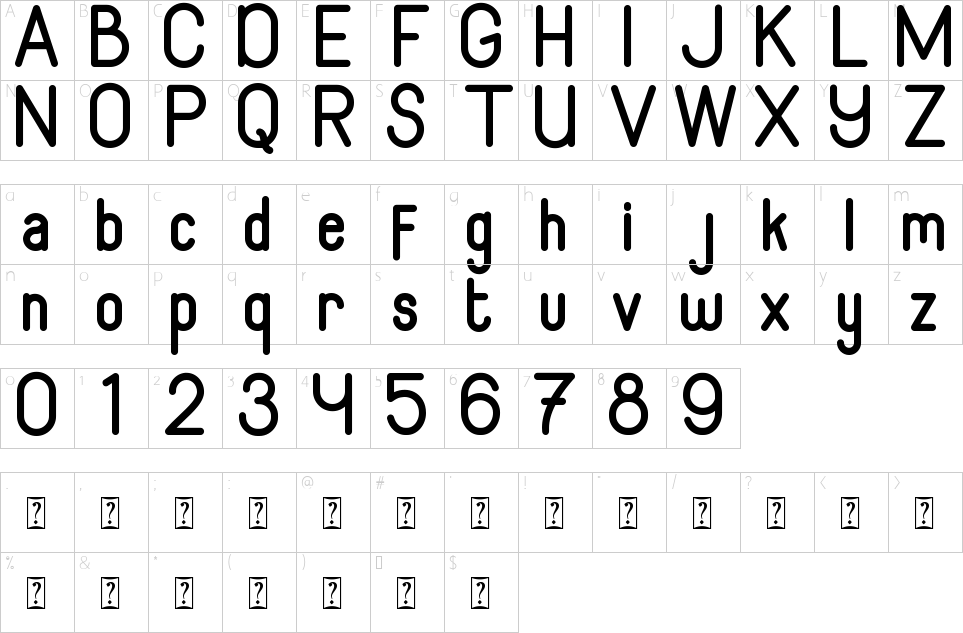
A fonte Algeko é uma escolha perfeita para designers e amantes da boa impressão. Desenhada pelo talentoso designer Alif Ryan Zulfikar, a Algeko traz uma combinação única de elegância e simplicidade. Esteve disponível gratuitamente para download, com mais de 2.529 pessoas optando por ela, o que indica a sua qualidade e versatilidade. A Algeko é uma fonte versátil, adequada para uso em diversos ambientes design, desde o layout de websites até editoriais de jornais. Com um design limpo e uma tipografia sofisticada, ela é uma ótima opção para qualquer projeto que busque um equilíbrio perfeito entre funcionalidade e beleza visual. A fonte Algeko não só oferece uma variedade de opções de estilo, como também mantém uma facilidade de uso que torna a criação de designs digitais uma experiência agradável e eficiente.